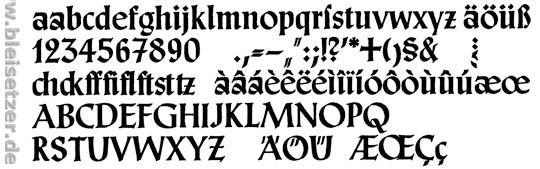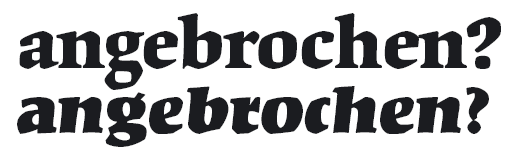
innovative, moderne Entwicklungen von Gebr. Schriften
Fallen euch evtl. ein paar gebrochene Schriften ein, die nach dem Zweiten Weltkrieg entstanden sind und die ihr für besonders innovativ haltet. Also keine Revivals bereits vorhandener klassischer Schriften, sondern gebrochene Schriften mit neuem Formprinzip.
Ich denke da zum Beispiel an:
die Leipziger Antiqua als Hybride zwischen Antiqua und Gebr. Schrift
oder an die TipToe von KLTF als Gebrochene Grotesk
die ITC Banco und noch schöner die Zalamander von Tim Ahrens
und die Fakir
(Also quasi auch Schriften, die nur eine gebrochene Schulter haben und auf dem ersten Blick nichtmal unbedingt als eine gebrochene Schrift zu erkennen sind)
Viele neue Frakturschriften finden sich im Buch »Fraktur Mon Amour«. Einfach mal danach googeln
Volcano-Type haben ja da ein paar Fonts zu bieten, wie zum Beispiel:
Frakturbo
Fraktendon als Hybrid
noch ein Fraktur-Hybrid
und natürlich die neue Blaktur von House Industries
Jap, ich such schon ein bissel länger :)
ist ein Studienjahrprojekt von der FH (Semester gibt es nichtmehr seit Einführung des Bachelors)
Ich hab die Texte jetzt noch mal ein kleines bißchen für den Abschluss umgeschrieben und bin deswegen jetzt auf der Suche nach ebensolchen Schriften.
Danke schonmal für die vielen Vorschläge. Und insbesondere danke, das ihr mich nochmal an die Kaas erinnert habt. Hätte die beinahe vergessen.
Aber viele der genannten Schriften sind eben nichts neues die meisten Schriften, wie zum Beispiel die Neutrum und die Auferstehung etc. verfolgen das Prinzip der Geometrisierung. Das Prinzip wurde schon um 1900 praktiziert.
Bei der Kaas ist das Prinzip ja quasi genau das selbe, das einzigst schöne an ihr finde ich sind die hebräischen Schriftzeichen. Weshalb sie eine Erwähnung wert ist.
Ich suche nach Schriften, die eine bis dato einzigartige Idee aufgreifen. Die von mir genannten Schirften sind vielmehr eigene Entwicklungen und beruhen auf mir zumindest keinem bekannten Prinzip. Deswegen fragte ich quasi, ob diese Schriften die Vorläufer sind, oder ob es schon frühere Bemühungen dieser Art gab.
Fraktur Mon Armour hab ich bereits zur Hand und die dort vorgestellten Schriften in der Abteilung Display sind meist quasi nur in FontLab verfremdete Schriften und beruhen daher meist nicht wirklich auf einer eigenen kreativen Leistung. Auch sind die Schriften teilweise eher Eintagsfliegen und daher nicht wirklich dass was ich als innovativ betrachte!??! Viele der dort vorgestellten Schriften sind auch einfach von minderer Qualität, weswegen ich diese Schriften deswegen auch ungerne in dem Artikel vorstellen möchte.
Ich finde die Blaktur zum Beispiel auch wunderschön, aber es ist quasi einfach nur eine stinknormale Textur.
Die Fakir hingegen ist nichtnur eine normale Textur, sondern eine Schriftfamilie mit 11 Schnitten, die für Display und den Textgebrauch "optimiert" worden ist.
Ich suche nach Schriften, die eine bis dato einzigartige Idee aufgreifen.
Die von mir genannten Schirften sind vielmehr eigene Entwicklungen und beruhen auf mir zumindest keinem bekannten Prinzip.
hmm. nenn oder zeig doch mal paar beipiele.
hier sind auch noch ein paar eher ungewöhnliche formen:
oder schau dich mal auf dieser bekannten freefontseite um, die
wir hier nicht nennen dürfen, da gibts noch mehr abgefahrene schriften.
ich sag nur blade- und unreal-schriftzug. überhaupt diese ganzen
bandlogos. ac/dc, sepultura, ironmaiden ...
informiere uns mal was aus deiner arbeit wird.
ich finde das thema ganz interessant.
Joa...
halt wie gesagt, die Fakir ist nicht nur eine normale Textur, sondern eine Schriftfamilie mit 11 Schnitten, die für Display und den Textgebrauch "optimiert" worden ist.
Dann noch:
Lapture.gif
Die Leipziger Antiqua aus dem Jahre 1971, bzw. ihr Revival Lapture von Tim Ahrens. Eine Hybridschrift, mit gebrochenen Schulter. Eine Mischung aus Antiqua und Textur.
Itc Banco aus dem Jahre 1951, quasi eine Schreibschrift mit gebrochener Schulter.
DIN sei grundsätzlich doof: (etwas überspitzt) wie kann
jemand eine klassizistische-Antiqua zeitgemäß im Jetzt
entwerfen, das ist doch schwachsinnig.
Ich mag die DIN, habe aber wie in diesem Beispiel gezeigt,
selber Schwierigkeiten.
PS: Es freut mich sehr, daß das Bild und somit der Name
heruntergeladen wurden, die Flintstone ist es nicht, die Kompakt ist super,
ist es aber auch nicht ...
Ich spiel kurz mit meiner Katze und löse das Rätsel auf.